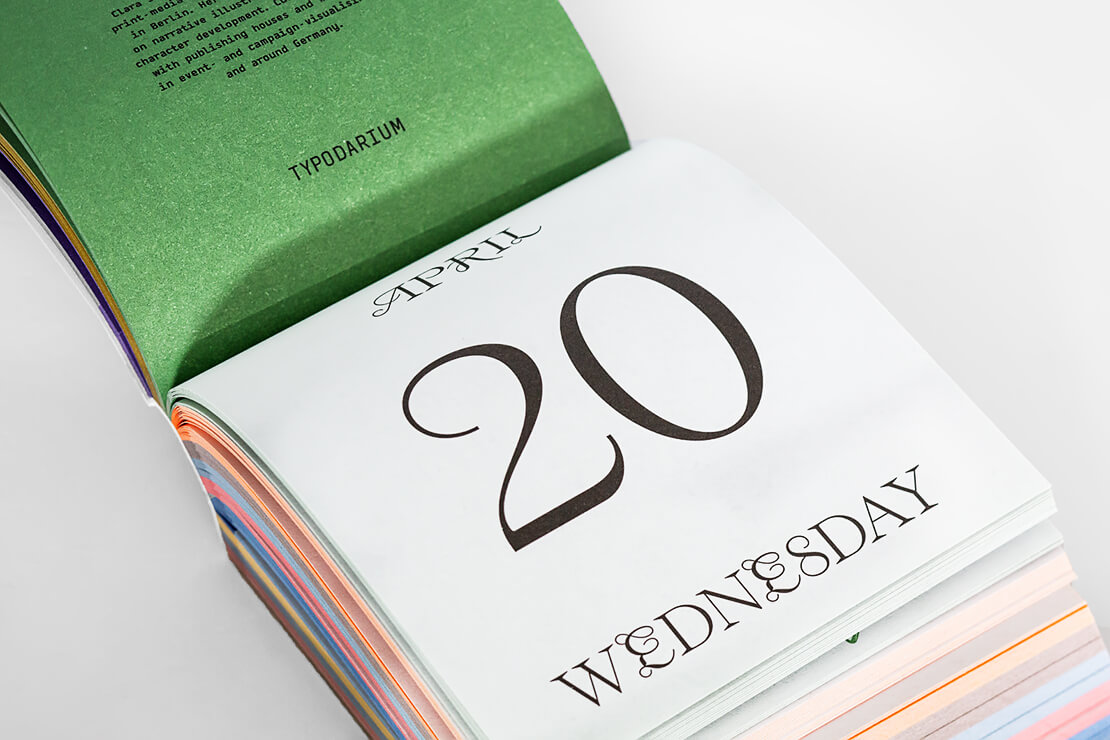
Typodarium 2022: Typografischer Abreißkalender
Das »Typodarium 2022« ist da. Lars Harmsen und Raban Ruddigkeit zeigen in dem typografischen Abreißkalender inspirierende Schriften für das kommende Jahr.
Auch in der neuesten Ausgabe präsentiert sich der Typo-Kalender in 12 fröhlichen Farben. Tag für Tag zeigt das Typodarium 2022 eine neue Schriftart, die zum Entdecken einlädt. So kommt man auf insgesamt 365 Schriften von 248 Designern aus 35 Ländern.
Die Tagesblätter im Typodarium 2022 enthalten jeweils Angaben zu Datum, Wochentag und ggf. Feiertag. Auf den Rückseiten werden die entsprechend verwendeten Schriftarten präsentiert. Außerdem findet man dort weitere Informationen zu Designer, Entwicklungsjahr sowie den Bezugsmöglichkeiten.
Frische und handgemachte Schriften im Typodarium 2022 Kalender
Neben trendigen Schriftarten, Brotschriften sowie ausgefallenen Lese- und Zierschriften gibt es zudem auch Handgemachtes zu entdecken. Auf den Blättern für Sonn- und Feiertage findet man nämlich Schriften, die mit Schere, Stiften, Klebebändern und Stempeln gestaltet wurden. Sie sollen einen kleinen Gegenpol zur digitalen Welt bieten.
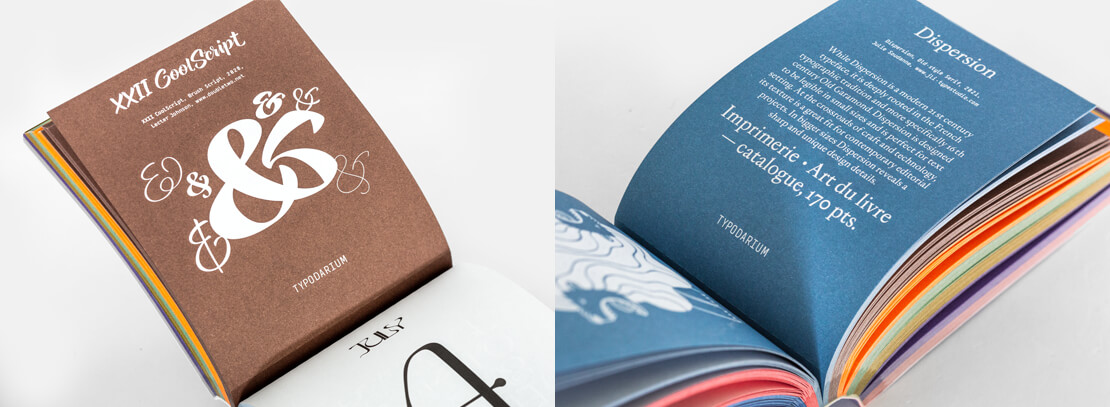
Als praktisch erweist sich zudem die mitgelieferte Sammelbox mit farbigem Überzug. Sie lässt sich zum Aufbewahren von abgerissenen Kalenderseiten verwenden. Auf diese Weise wird aus dem Typodarium 2022 nach und nach ein kleines Musterbuch mit persönlichen Schriften-Highlights.